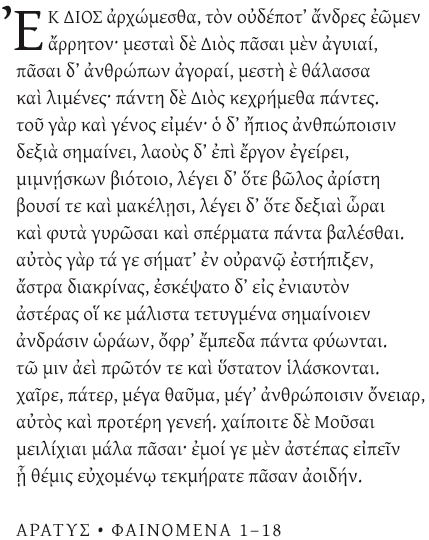
es sucht font greek Palatino Linotype
im letzen Tagen bin ich mit Theologiedoktorarbeit beschaftigt. Um greek Worte zu schreiben brauche ich Palatino Linotype. Leider habe ich noch dieses Buchstabe auf meinem Computer installiert. Wo kann ich es finden im internet? Gibt es jemand, die mir helfen kann?
"Palatino Linotype" war mindestens bei Windows 2000 dabei, evtl. bei anderen Windows-Versionen auch noch. Auch auf dem Mac kam sie ab Mac OS 7 als Systemschrift mit. Also schau doch mal, ob sie nicht sogar schon auf dem Rechner installiert ist und nur aktiviert werden müsste.
Muss es genau diese Schrift sein, oder geht es vor allem darum, dass du die griechischen Buchstaben brauchst? Zum Beispiel die Gentium hat die nämlich auch.
Die griechischen Zeichen findest du bei vielen Schriften.
Für eine Arbeit in Theologie benötigst du aber m. E. auch die polytonischen Glyphen. Es gibt relativ wenig Schriften, die diese Zeichen beinhalten.
Von Adobe:
Garamond Premier™ Pro, Minion, Arno Pro
Hier findest du passende Free-Fonts, die gut geeignet sind.
die palatino finde ich für komplette arbeiten zu breit laufend, fast zu kalligraphisch. gerade im gemischtsprachigen satz ist sie für mich sehr anstrengend.
bei mufi findest du auch noch andere schriften, die sehr umfangreich ausgebaut sind.
Für eine Arbeit in Theologie benötigst du aber m. E. auch die polytonischen Glyphen. Es gibt relativ wenig Schriften, die diese Zeichen beinhalten.
Deshalb hab ich ja die Gentium vorgeschlagen:
Je nach Version hast du da nämlich auch alles was du brauchst. Dafür gibt es nicht so viele Schriftschnitte wie z.B. bei der Arno Pro.
Mit meinem Beitrag wollte ich direkt ormom ansprechen – ist nicht als Antwort auf dein Schriftbeispiel gedacht. Auch ich finde die Gentium als sehr gut geeignet.